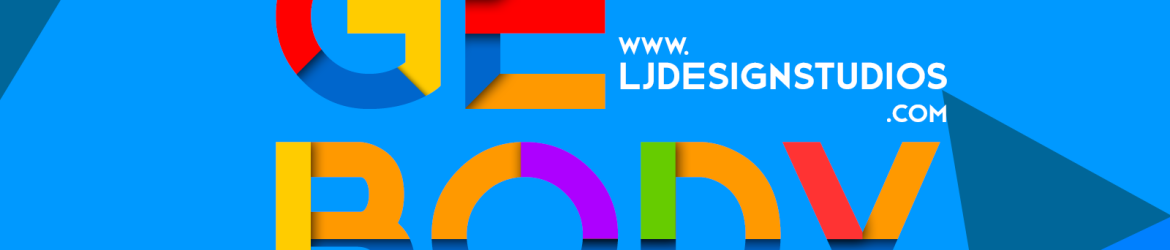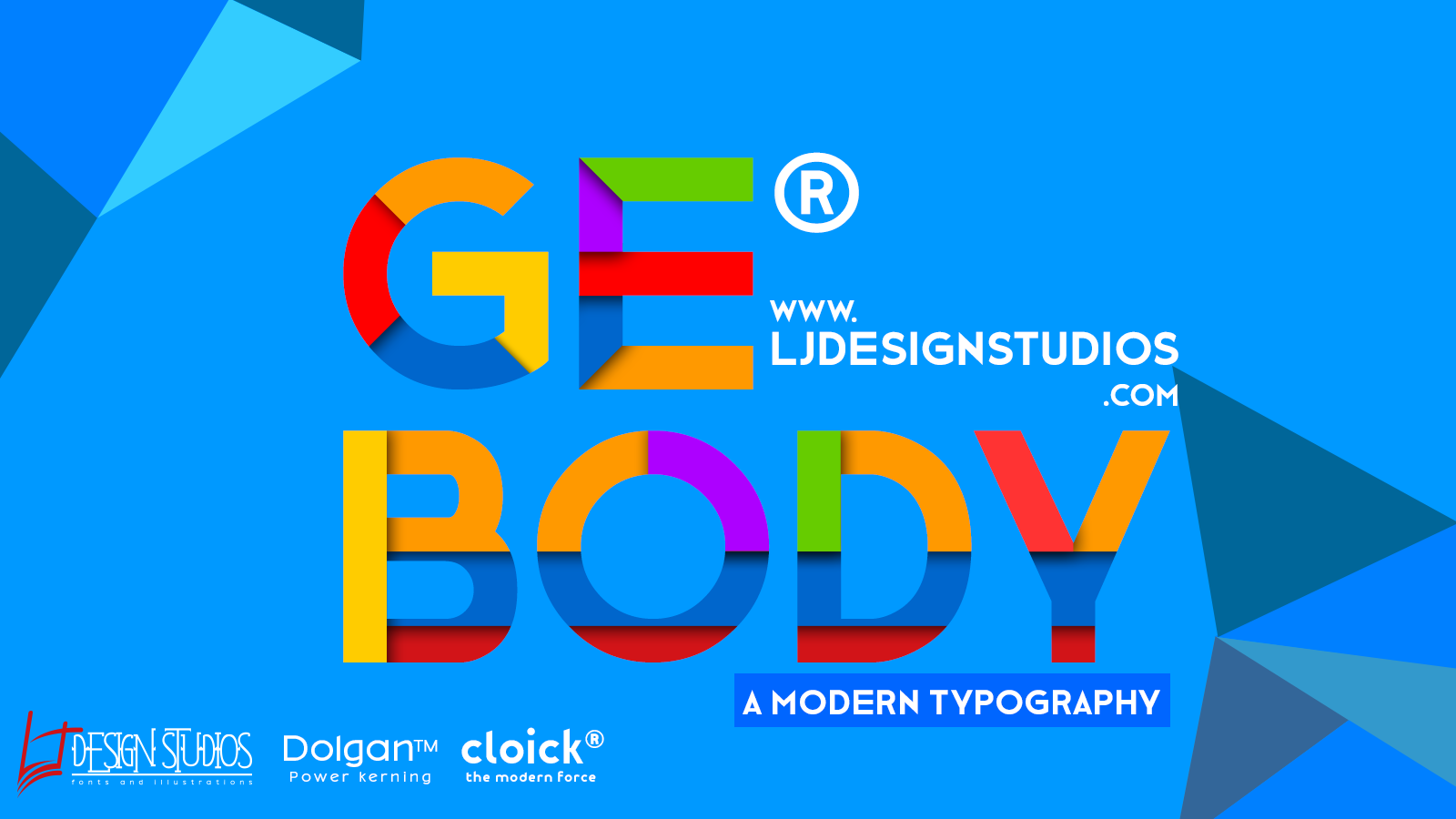
GE BODY FONT – Fonte Grátis
GE BODY FONT
Esta fonte ‘GE BODY FONT’ foi projetada sob uma licença de código aberto, permitindo que você a obtenha gratuitamente. Seu designer, lj.design, oferece ao público um tipo sem serif totalmente livre e disponível para qualquer uso, desde o design gráfico até a criação de conteúdo digital. Esta fonte é perfeita para designers amadores e profissionais que buscam uma opção clean e moderna para suas projetos. Com seu traço limpo e elegante, ‘GE BODY FONT’ oferece uma excelente combinação para criar texturas distintas em designs web, publicações ou até mesmo gráficos de papel.